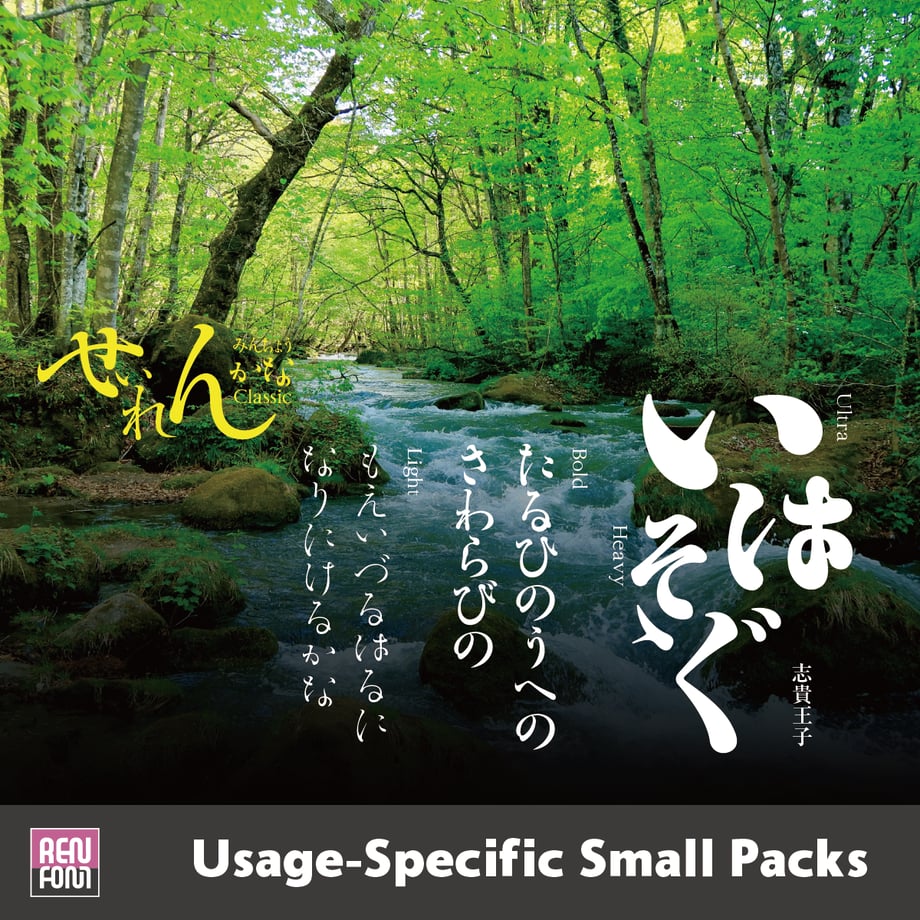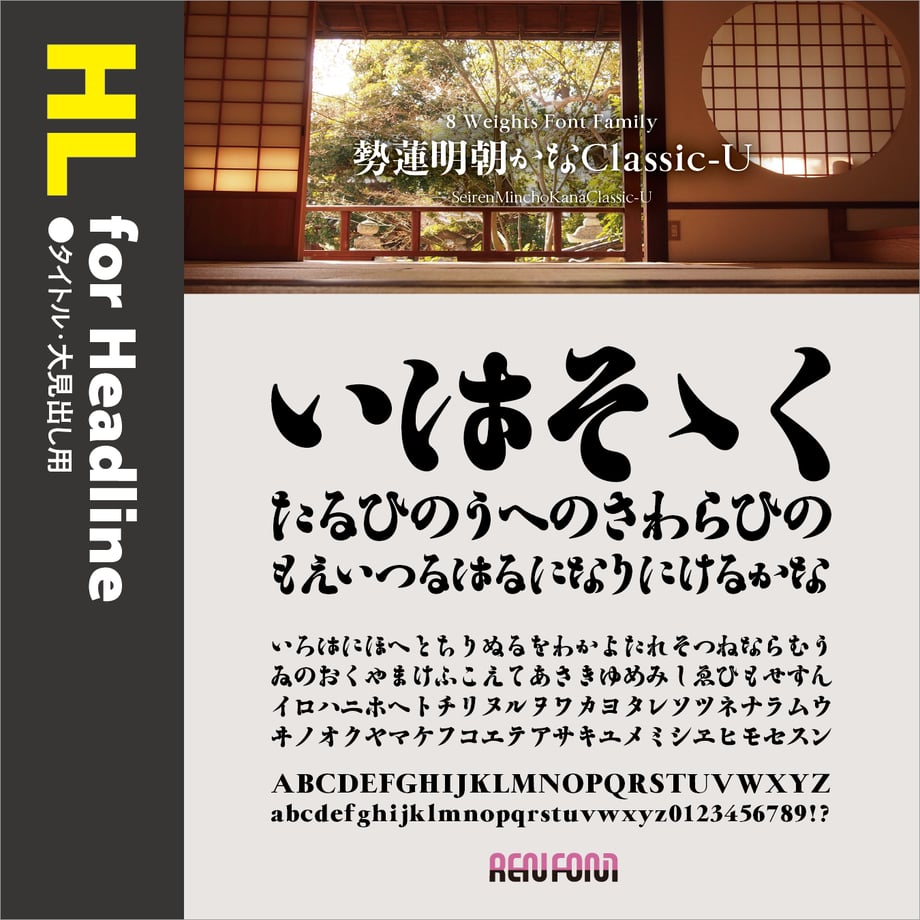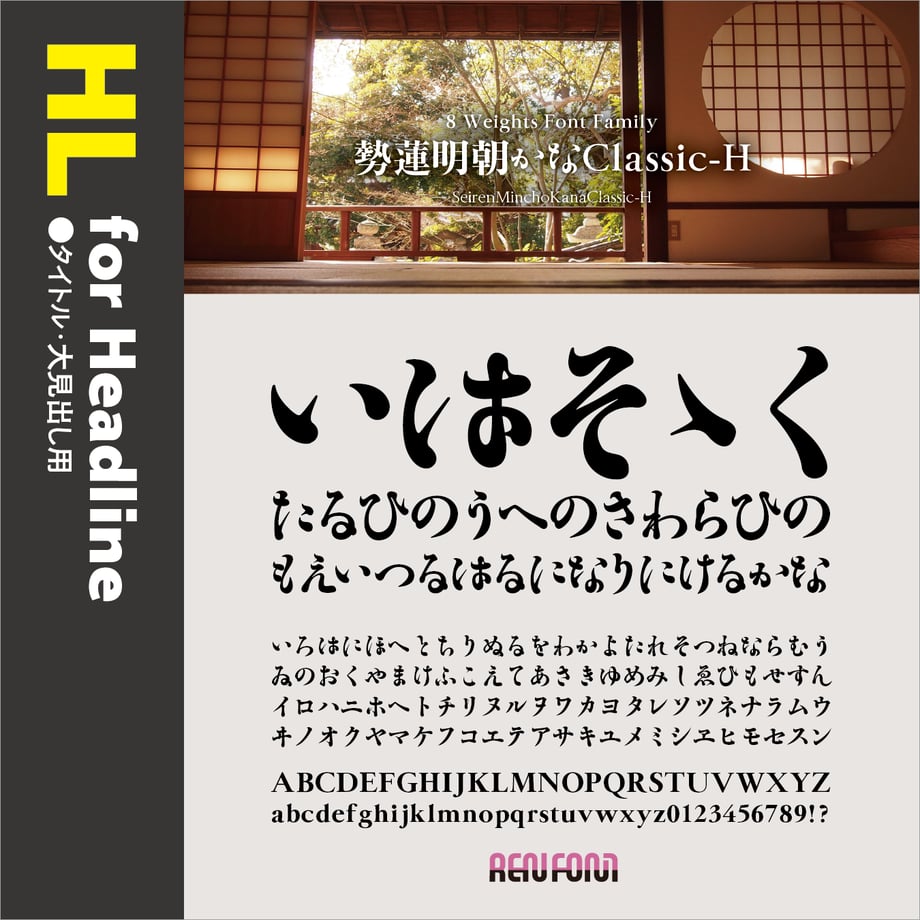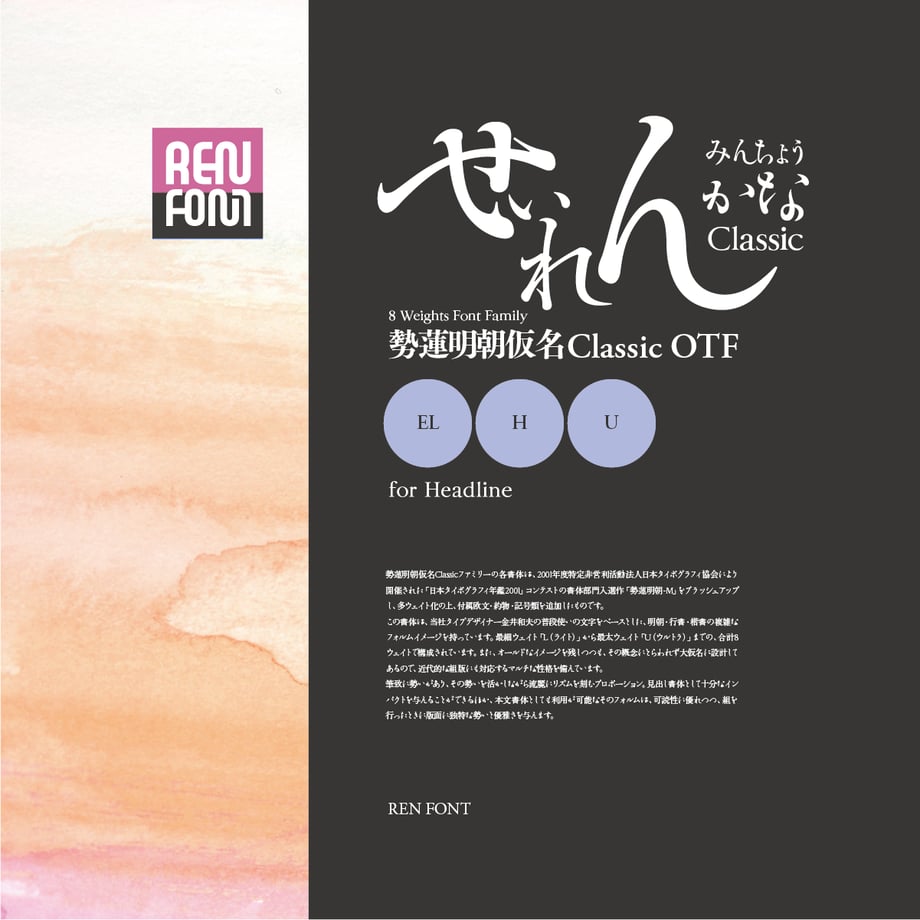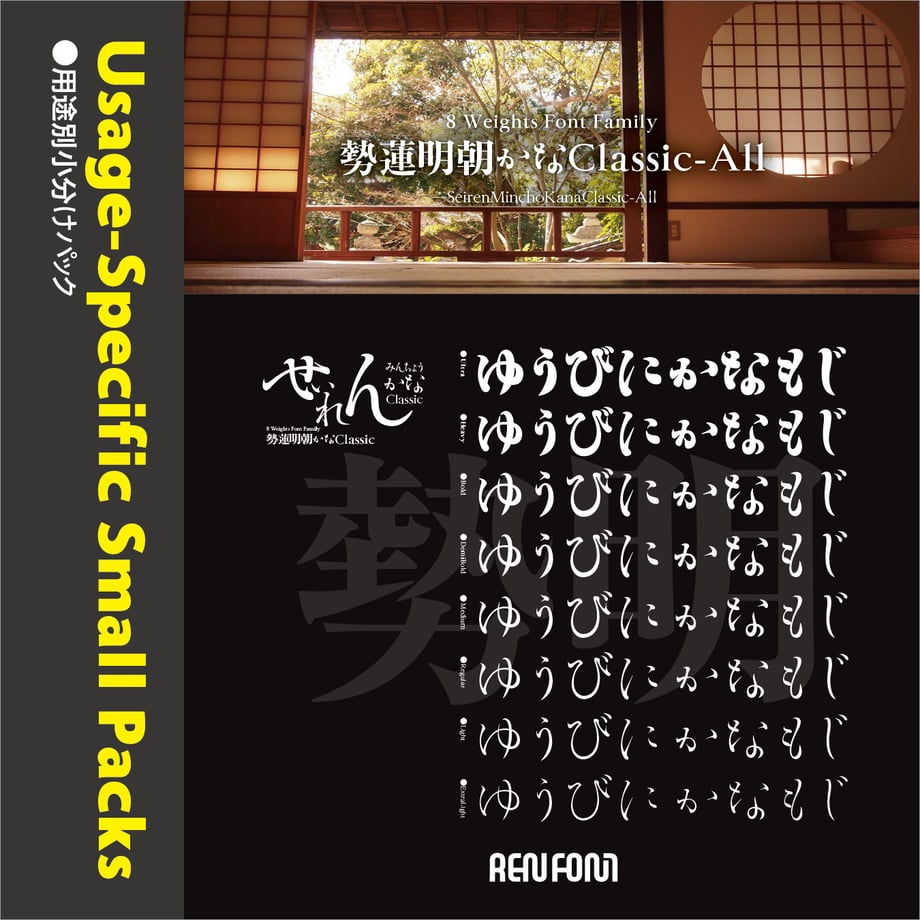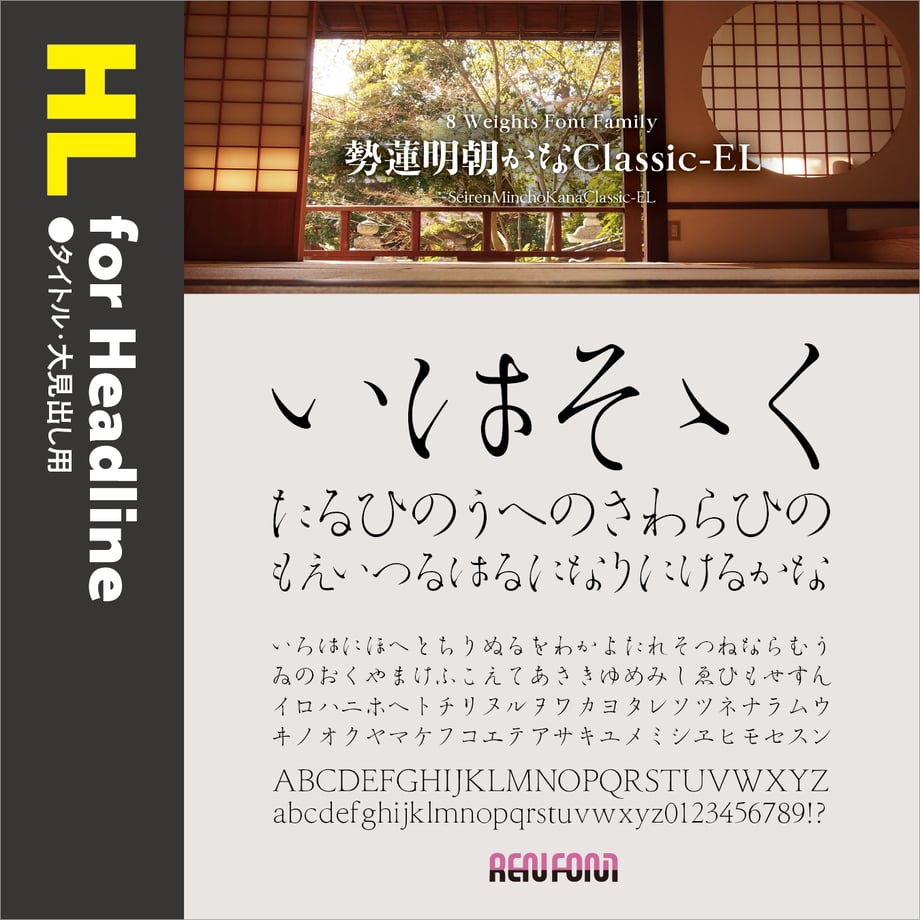
勢蓮明朝仮名Classic-HL(タイトル・大見出し用)EL/H/U
可読性に優れ勢いと優雅さを兼ね備えた
勢蓮明朝仮名Classic 8ウェイトファミリー / OpenType
勢蓮明朝仮名Classicファミリーの各書体は、2001年度特定非営利活動法人日本タイポグラフィ協会により開催された「日本タイポグラフィ年鑑2001」コンテストの書体部門入選作「勢蓮明朝-M」をブラッシュアップし、多ウェイト化の上、付属欧文・約物・記号類を追加したものです。
この書体は、当社タイプデザイナー金井和夫の普段使いの文字をベースとした、明朝・行書・楷書の複雑なフォルムイメージを持っています。最細ウェイト「L(ライト)」から最太ウェイト「U(ウルトラ)」までの、合計8ウェイトで構成されています。また、オールドなイメージを残しつつも、その概念にとらわれず大仮名に設計してあるので、近代的な組版にも対応するマルチな性格を備えています。
筆致に勢いがあり、その勢いを活かしながら流麗にリズムを刻むプロポーション。見出し書体として十分なインパクトを与えることができるほか、本文書体としても利用が可能なそのフォルムは、可読性に優れつつ、組を行ったときに版面に独特な勢いと優雅さを与えます。
明朝体の形状を基本にしていますが、行書・楷書のイメージも含んでいます。
作者の普段使いの文字をアレンジしてあるので、明朝のセオリーを外した筆勢も随所にあり、強い個性と主張を発揮します。
起筆や払い、跳ねの細い先端は、丸く処理してあり、ソフトさもさりげなく持ち合わせています。
文字の高さや横幅がフォントの概念を覆すほどバラエティに富んでいるので、一文字ずつばらしてサイズに強弱をつけると、見出しとしてあたかも書道のような最大限の効果を得られます。
また、本文組にも既存の漢字と組み合わせてよく調和します。
欧文・数字は、特徴の強い両仮名に合わせて独自にデザインしました。
格調高いGaramondに近い形状をもっていますが、手書きの風合いを出すために、エクスハイトを高めに設定したり、セリフを短めにして、あえてアンバランスさを強調しています。